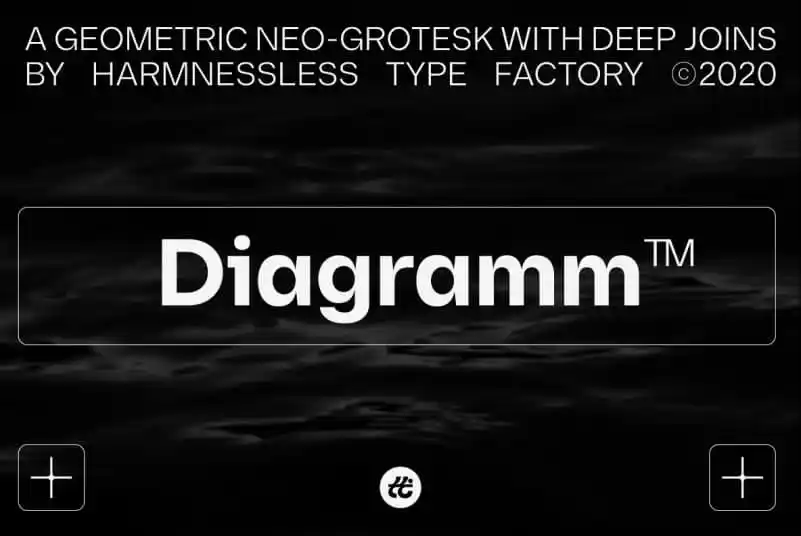
Diagramm Sans Serif é uma fonte sans-serif que traz aos designers a oportunidade de adicionar um toque de elegância à suas criações. Inspirada na arquitetura geometrica dos neo-groteskus, essa fonte apresenta linhas geométricas e detalhes cuidadosamente finos, criando um estilo moderno sem perder a beleza clássica. Desenvolvida pela HarmnesslessType, esta fonte é perfeita para quem busca uma combinação única de simplicidade e sofisticação. Com 18 pesos, incluindo as variações de linhas esbatidas até o bold, Diagramm Sans Serif oferece um leque amplo de opções para adaptar ao seu projeto. Se parecer familiar, é porque a essência da fonte permanece inalterada; ela mantém os aspectos contemporâneos e modernos que fazem dela uma escolha inteligente para qualquer design. Perfectamente complementa elementos gráficos tradicionais ou criativos na web, dando um toque distintivo aos seus projetos.